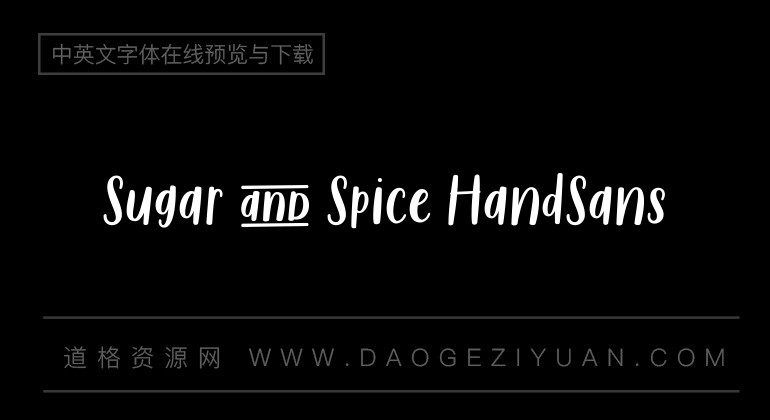
Sugar & Spice HandSans
Sugar & Spice HandSans是一款由字体设计师Alex Joganic于2020年发布的手写风格字体。该字体具有圆润、自然、温馨的特点,适用于卡片、海报、包装设计等很多场合。 Sugar & Spice HandSans字体包括58个字符,包括26个英文字母、数字、标点符号和一些特殊符号,支持英语、西班牙语、德语、意大利语和葡萄牙语。 此外,Sugar & Spice HandSans字体还包括了斜体和粗体版本,使得设计师可以更好地运用该字体来满足设计需求。 总的来说,Sugar & Spice HandSans是一款非常适合用于需要传达亲切、轻松氛围的设计中的字体。
Sugar & Spice HandSans是一款非常不错的手写艺术字体,具有很好的视觉感,适合于文化类的宣传设计、商业类品牌的广告和产品包装设计以及个性化文字排版等较多场景。